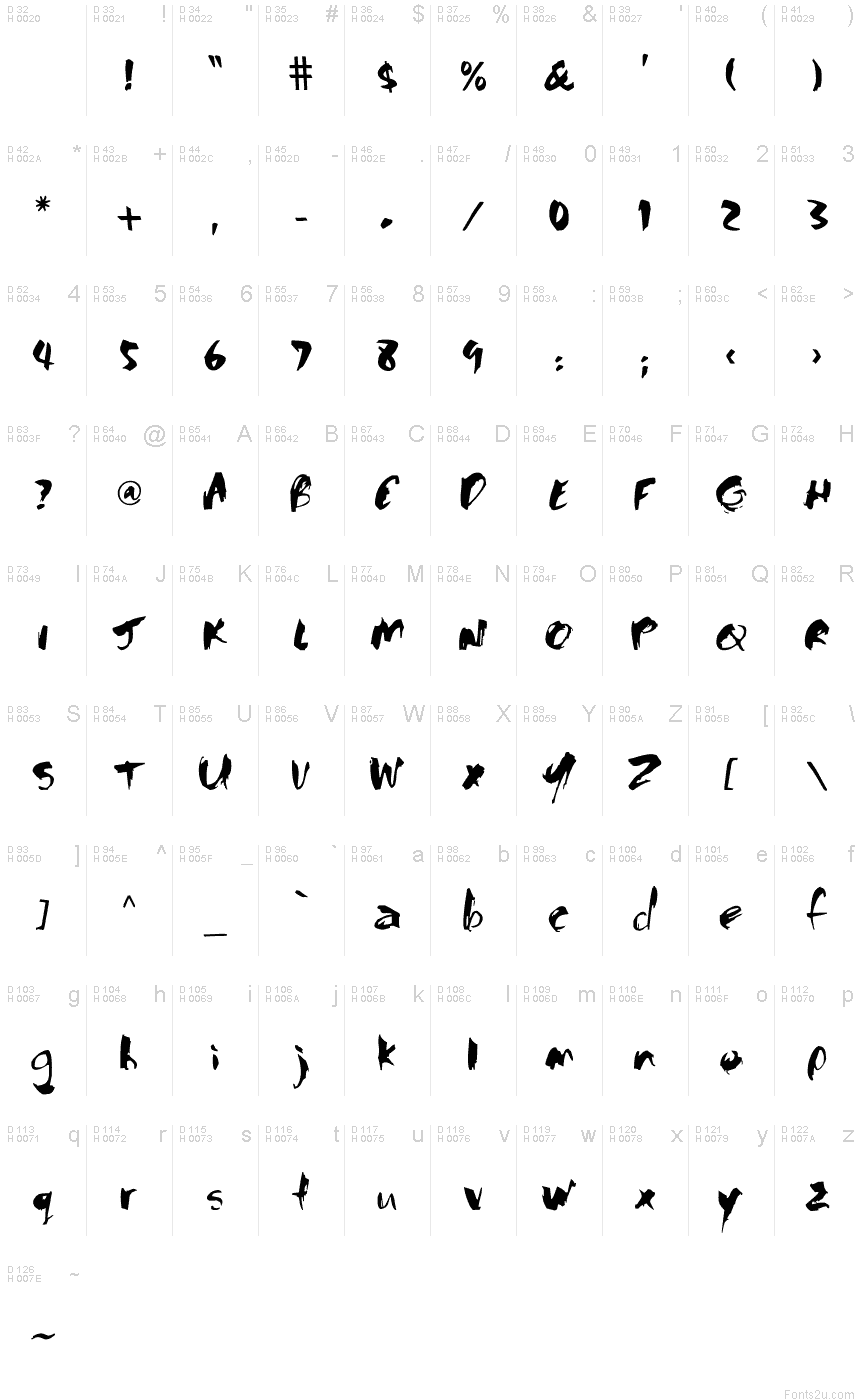
VNI-Thufapfan Normal
VNI Thufapfan od HungLan Artdesign to darmowy font display typu brush o surowym, poszarpanym rytmie. Litery wyglądają jak wycięte szerokim, niecierpliwym pociągnięciem, łącząc masywne bloki, ostre kolce i nierówne krawędzie, co nadaje całemu krojowi napiętą, ręcznie wykonaną energię.
Ten darmowy font sprawdzi się wszędzie tam, gdzie typografia ma brzmieć pilnie i nieco niepokornie – nagłówki plakatów, oprawa muzyczna, okładki zinów, plansze tytułowe czy krótkie logotypy pasują do niego idealnie. Najlepiej prezentuje się w krótkich słowach i zwartych liniach, gdzie tępe kształty i nagłe punkty robią wrażenie bez potrzeby zajmowania dużej ilości miejsca.